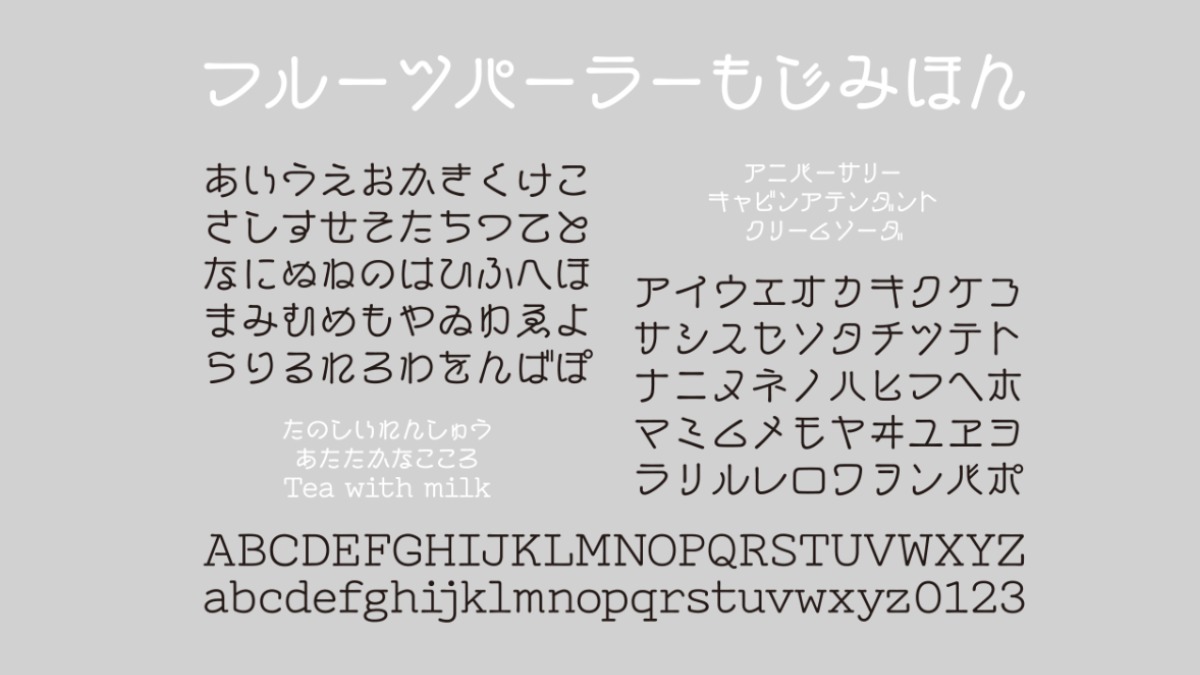
フルーツパーラー mini Rは、大正時代の文字からインスピレーションを得て作成されたレトロな雰囲気の日本語フリーフォントです。レトロな雰囲気を持ちながらも、現代にもピッタリとマッチする使いやすいフォントで、手描きのニュアンスがやさしい雰囲気で、デザインに温かみと懐かしさを加えます。
フルーツパーラーmini Rは、横書き専用のお試し版になります。商用版と異なり縦書きや異体字、アルファベットが無く、「いえイエ」の文字が「ゐゑヰヱ」になります。商用で利用するには、製品版を購入する必要があります。
フルーツパーラー mini Rの詳細情報
| 書体名 | フルーツパーラーmini R |
| 収録文字 | カタカナ ひらがな 数字 |